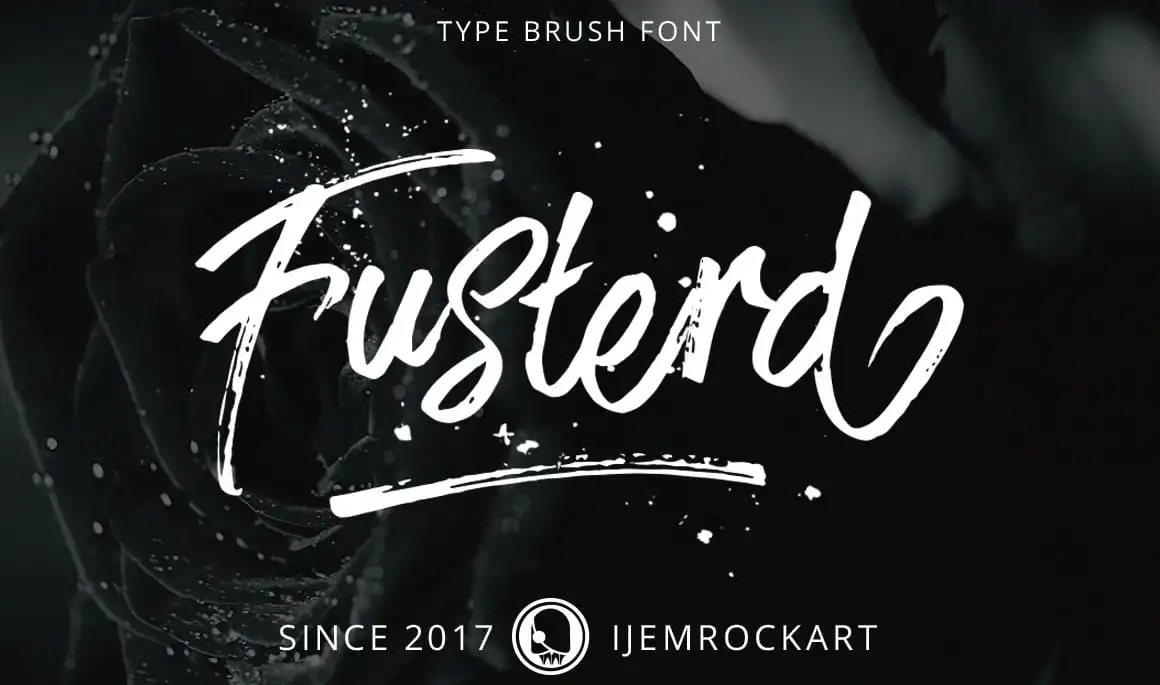
Fusterd Brush Font – Download Grátis
Olá! Estou aqui a introdução à Fusterd – uma tipografia com traço brush. Fusterd foi projetada pelo Ijemrockart e compartilhada pela Pathero Studio. O Font de Fusterd é um tipo moderno e contemporâneo, cheio de estilo, que você estava procurando. Ele oferece um fluxo único e a fonte script de Fusterd é um traço brush criado à mão com uma esponja e tinta, sendo grosso e irregulares no linhamento. Através do uso deste tipo, ficará perfeitamente adaptado para projetos que exijam design em estilo de águacolor ou letras de mão forte. Idealmente, você pode usá-lo em elementos de blog, postais, elementos de casamentos, camisetas e roupas, capas de livros, cartões de convite, marcas de empresa, cartões de agradecimento, marcações e citações artesanais. Fusterd é uma excelente escolha para estilos criativos que exigem um traço brush com certa personalidade. Este tipo se adapta perfeitamente tanto em design digital quanto em gráficos manuais, proporcionando-lhe liberdade de expressão sem perder a qualidade e os detalhes essenciais.